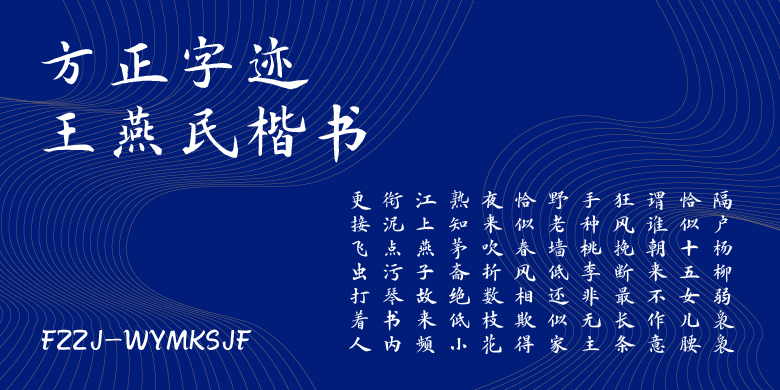
方正字迹-王燕民楷书
字体品牌: 方正字迹 设计师:王燕民 字体分类:常规书写·毛笔 字体属性:精品字 字符集:大陆简体(GB2312-80)、简繁扩展(GBK) 发布时间: 2021
《方正字迹-王燕民楷书》是由中央电视台资深美术指导、国家一级美术师、著名书画家王燕民先生书写创作的。字体以清丽雅正为主旨,结体严谨整饬,笔画舒展劲秀。骨气峻朗,平和静穆,散发出蕴藉涵泳的书卷气息。适应面较广,最宜温润和谐的语义表达。